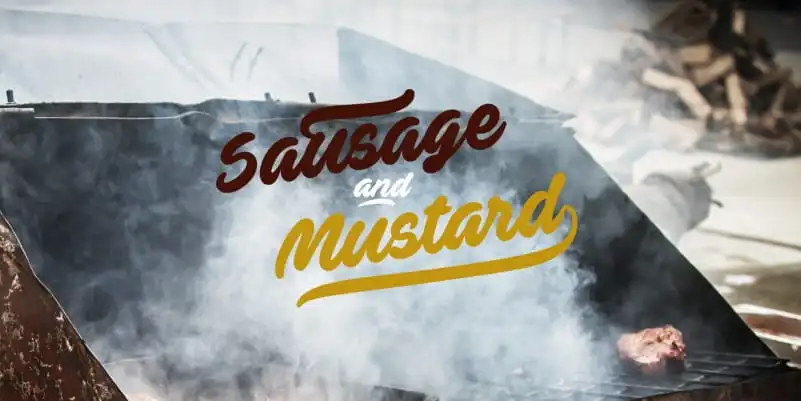
Ave Bold Script Font – Fonte Grátis
Ave Bold Script Font
Esta fonte ‘Ave Bold Script Font’ traz um toque natural para seus projetos design, com detalhes meticulosamente cuidados. Ela é uma tipografia script leve e suave, ideal para adicionar um ar elegante e sofisticado a seu trabalho. A fonte vem em três graduações de espessura: a fina Ave Utan, a média Ave Betwan e o grosso/fatavo Ave Fedan. Suas linhas fluidas e perfeitas harmonizam perfeitamente com qualquer projeto que você esteja desenvolvendo. Seja um site elegante ou uma identidade visual criativa, esta fonte é sua melhor aliada para criar algo único e de alta qualidade. Prove a beleza da natureza em cada detalhe.